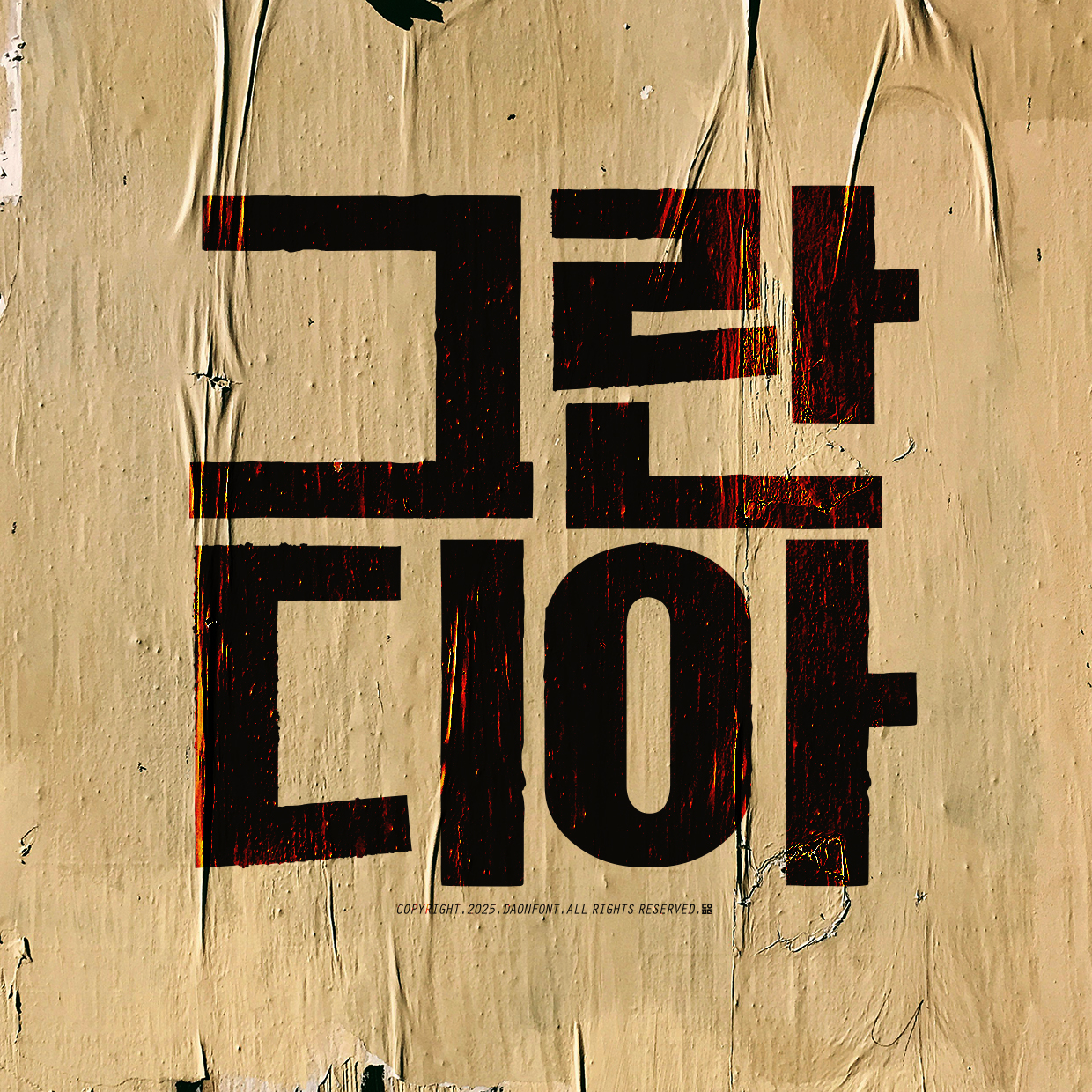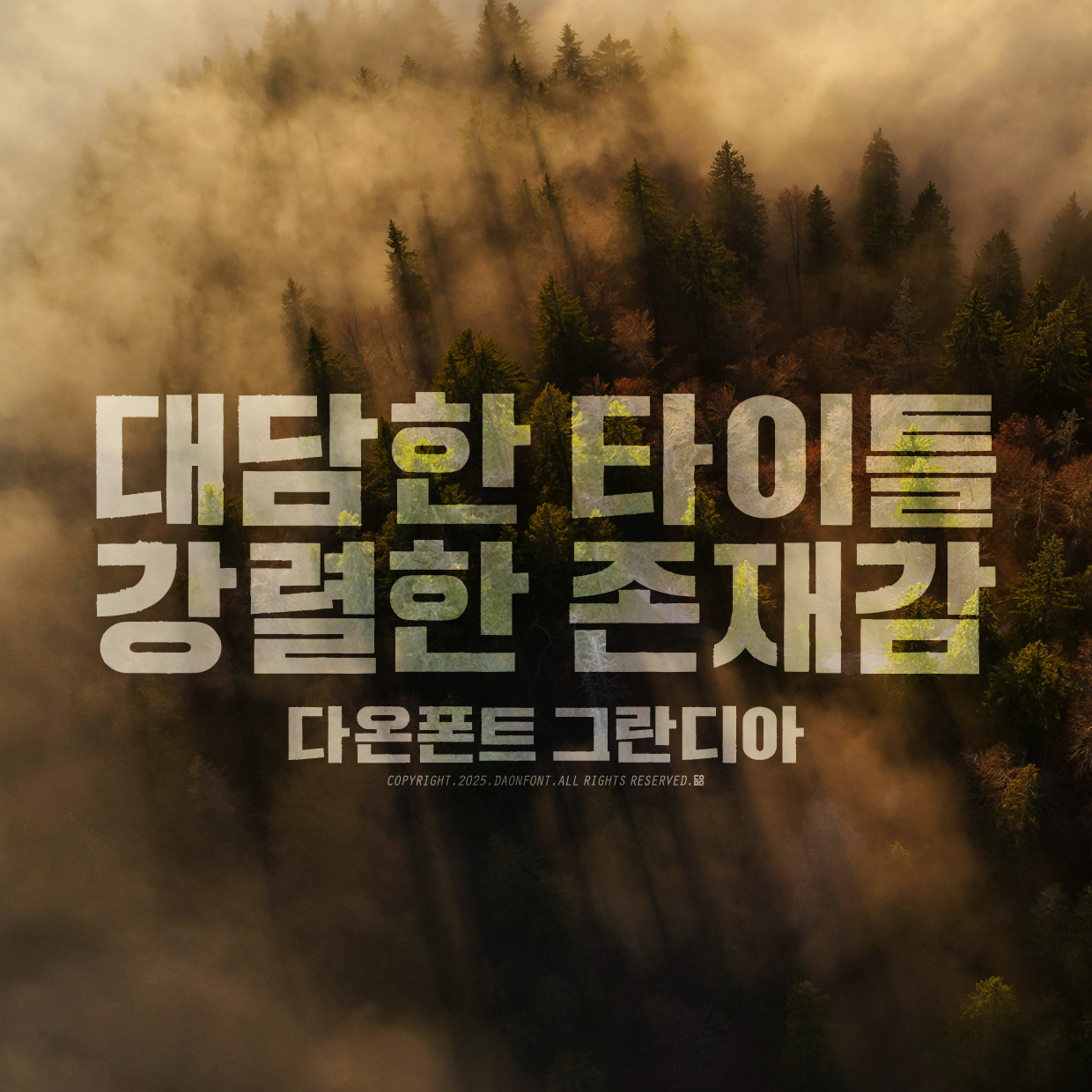
신규폰트 "그란디아"가 제작 중입니다.
그란디아, 첫 번째 획을 새기다.
강렬한 타이틀을 위한 새로운 서체, 그란디아의 자소디자인이 마무리되었습니다.
각진 나무를 먹물에 묻혀 한지에 하나하나
힘을 실어 찍어내며, 기본 획을 완성했습니다.
붓이 아닌, 단단한 재료로 찍어내는 과정에서 생기는 거친 질감과
묵직한 획의 흐름이 그란디아만의 독창적인 개성을 만들어갑니다.
이제 서체가 점점 모습을 갖춰갑니다.
곧, 더 완성된 형태로 찾아뵙겠습니다.